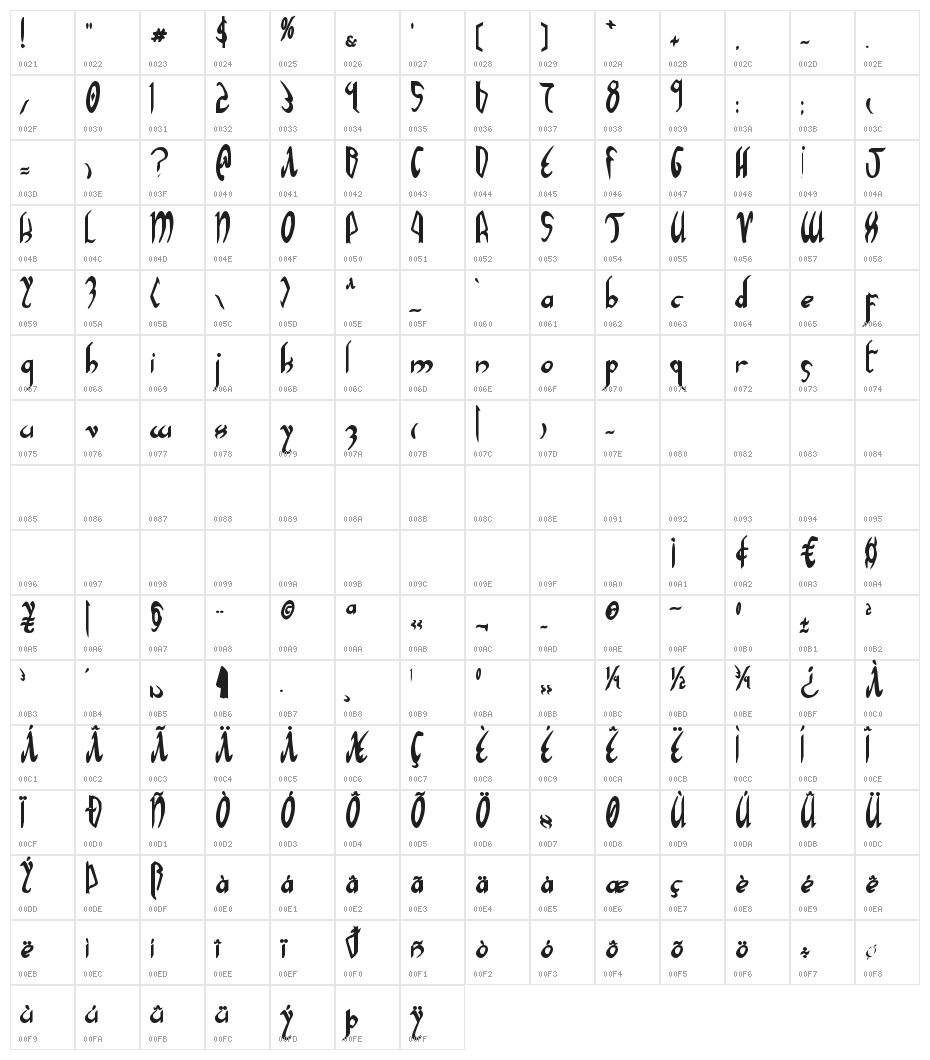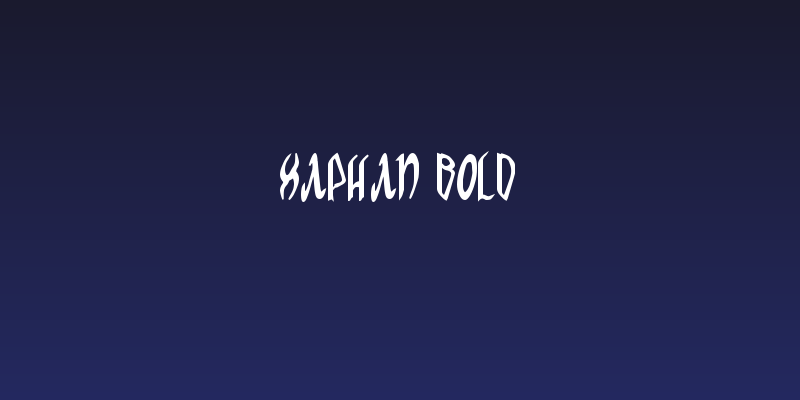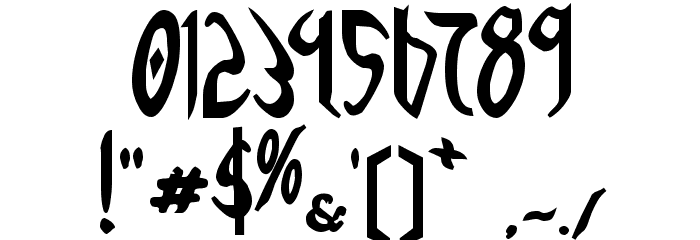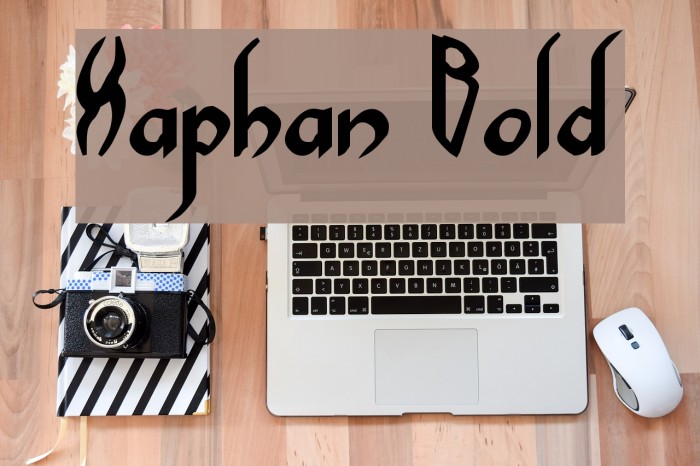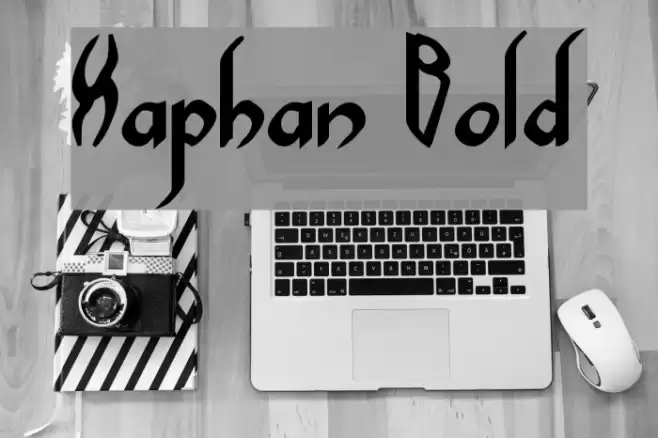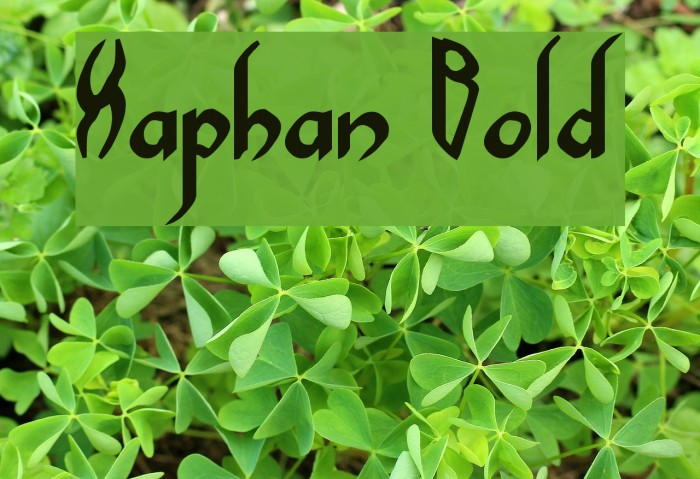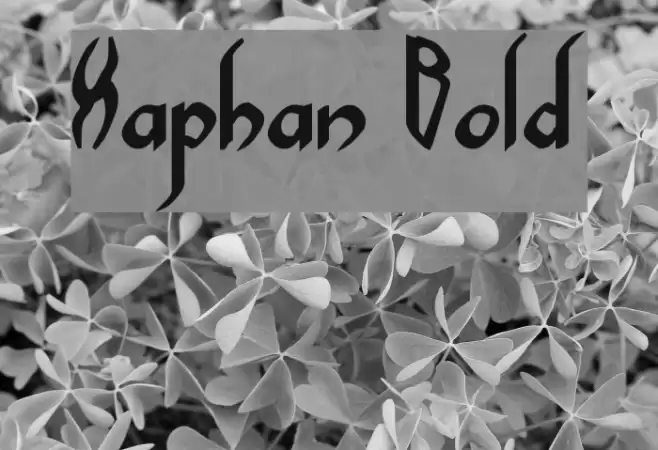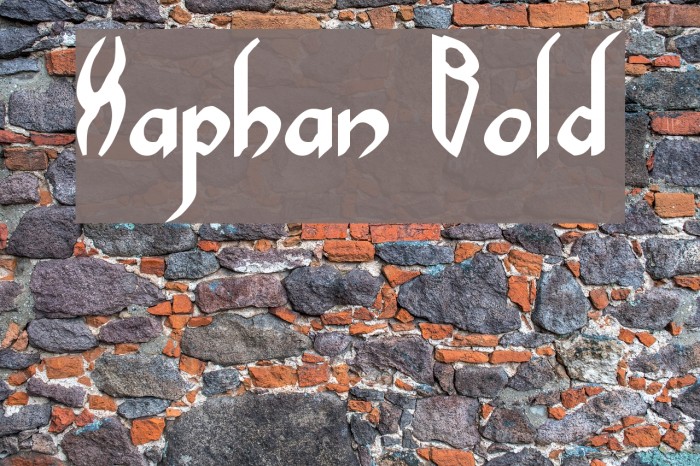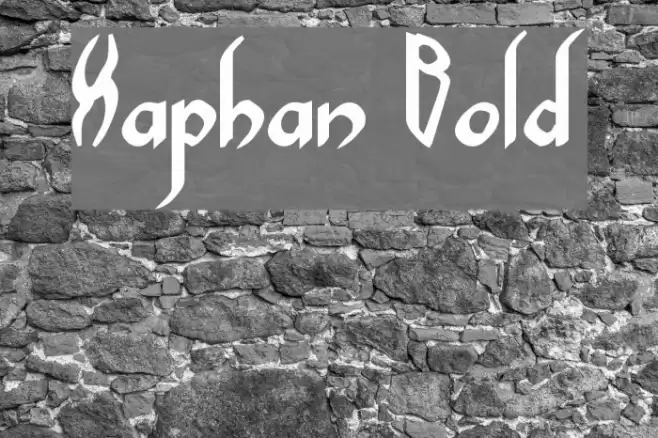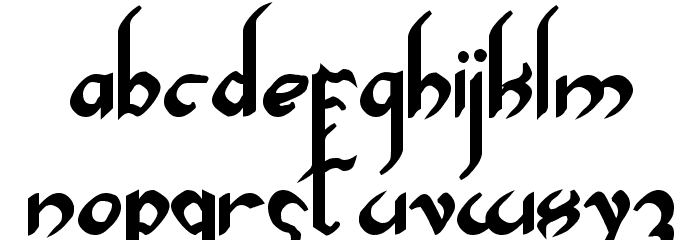
Xaphan Bold Font
✎ Gothic
| Stil general | Gothic, Dramatic |
| Proiecte propuse | Ideal for use in fantasy-themed designs, book covers, posters, and branding that requires a bold and dramatic impact. |